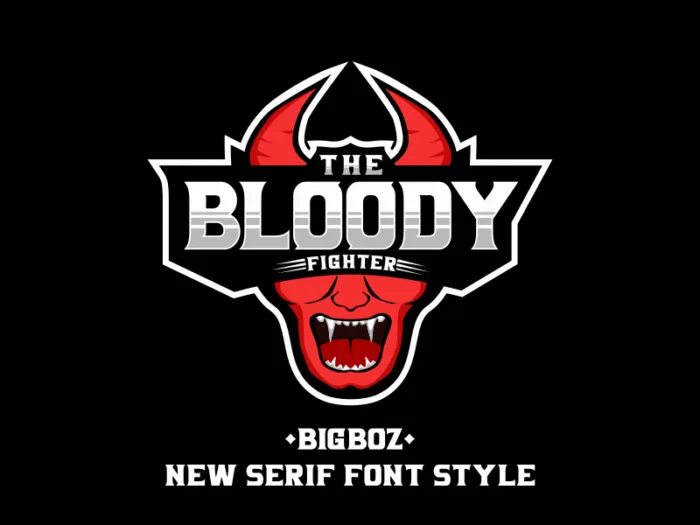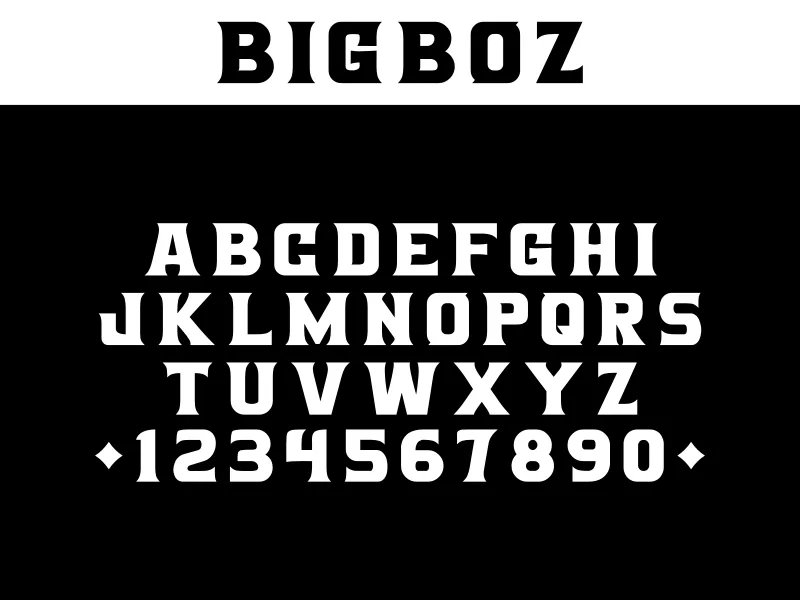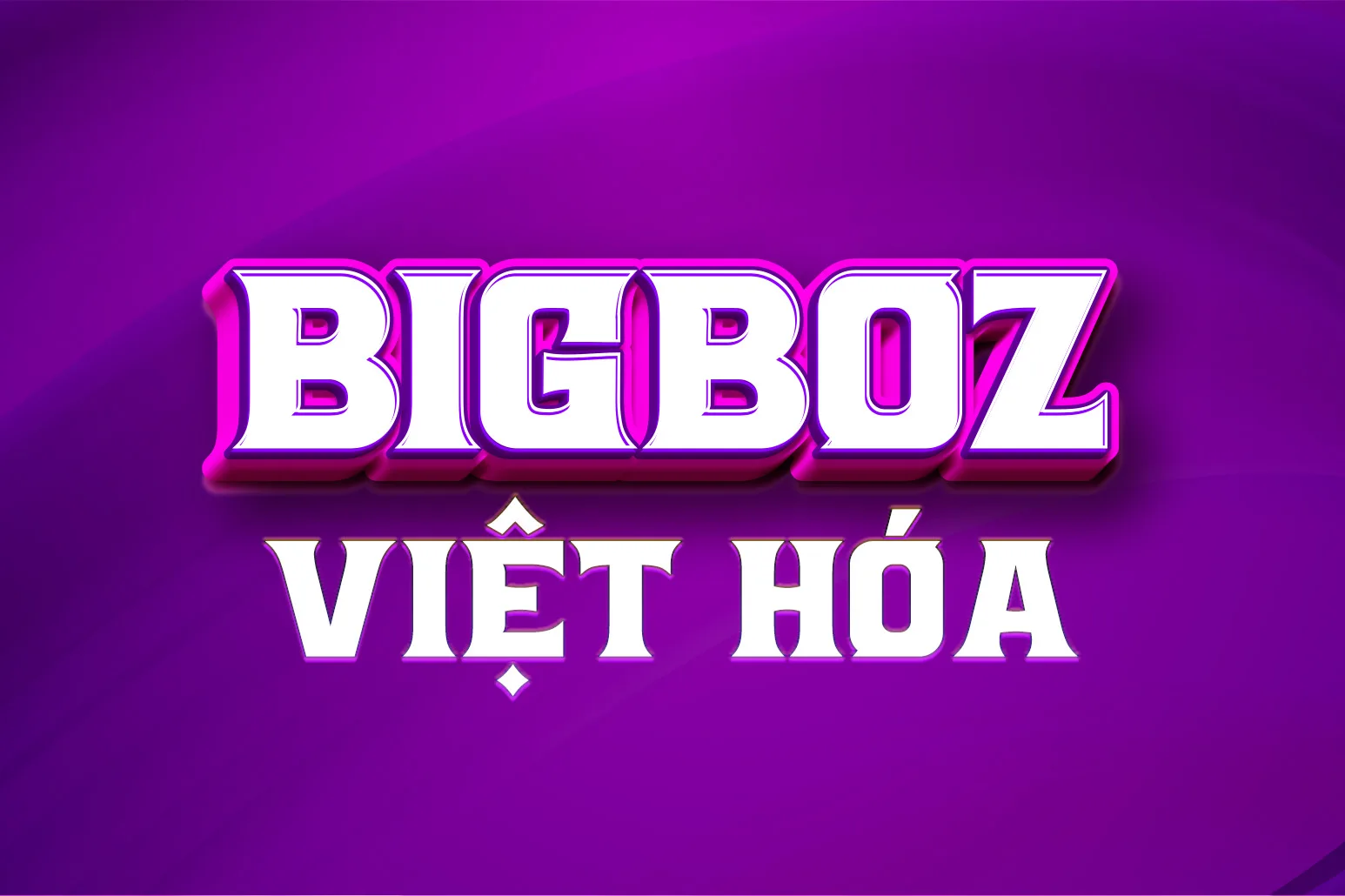
DVN BigBoz Việt hóa – Font chữ phong cách công nghệ, năng động và hiện đại
DVN Bigboz Việt hóa là kiểu chữ tiêu đề đậm nét, thiết kế với cấu trúc mạnh mẽ, góc bo vuông vức cùng đường nét cắt xẻ dứt khoát. Font mang phong cách đậm chất nam tính và công nghiệp, phù hợp với các thiết kế poster, tiêu đề, logo hoặc thương hiệu cần tạo ấn tượng thị giác mạnh mẽ. Các ký tự được tinh chỉnh với trọng số nặng, giúp font nổi bật ngay cả ở kích thước nhỏ. Bộ font đã được Việt hóa đầy đủ dấu và ký tự tiếng Việt, giữ nguyên phong cách nguyên bản mạnh mẽ, đồng thời tối ưu cho cả in ấn lẫn hiển thị số.
Gợi ý sử dụng:
• Poster phim hành động
• Bìa album nhạc rap/hiphop
• Logo thời trang đường phố hoặc thương hiệu cá tính
• Typography headline và banner quảng cáo
• Dự án banner, logo thể thao
• Dự án xe cộ, tốc độ
• Dự án khoa học công nghệ